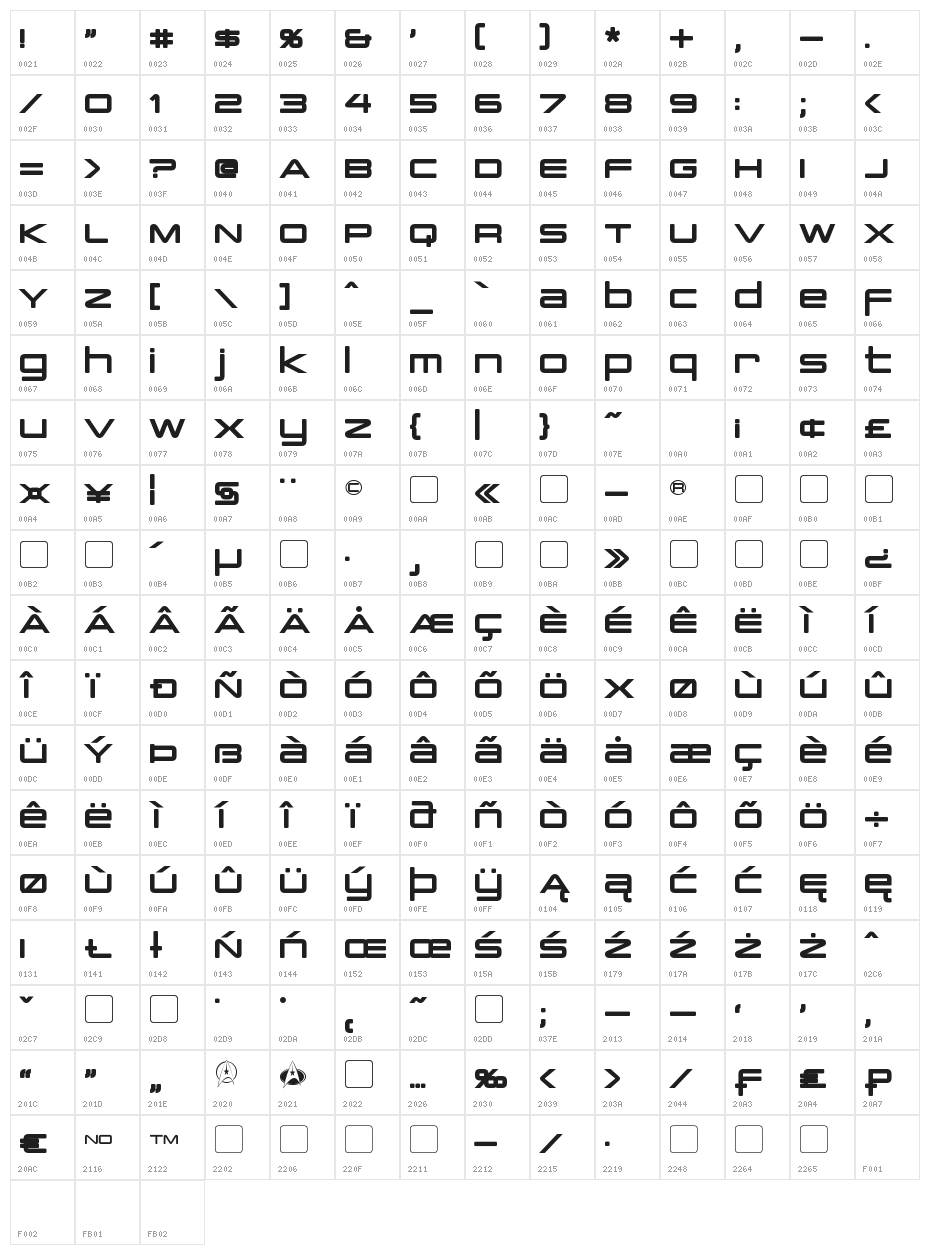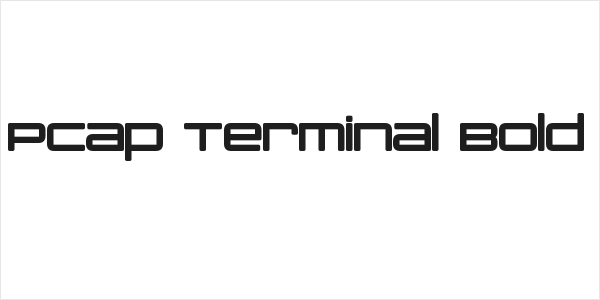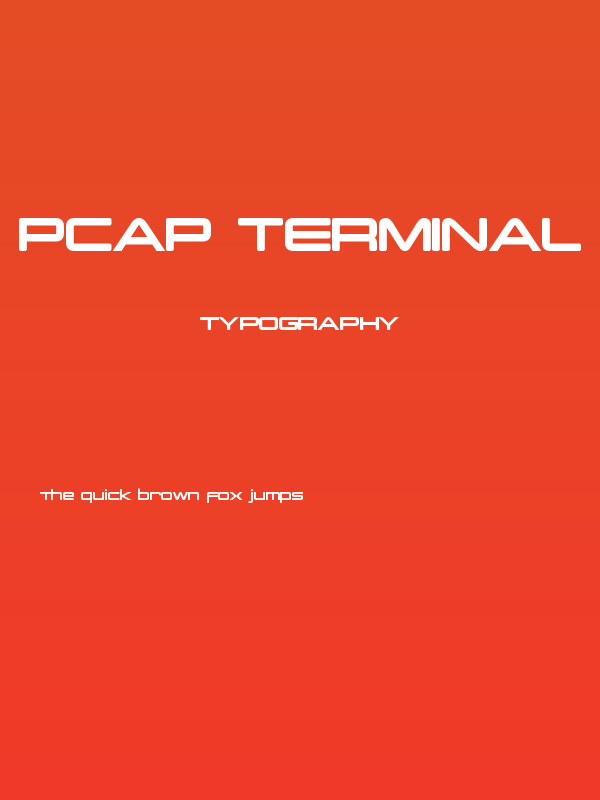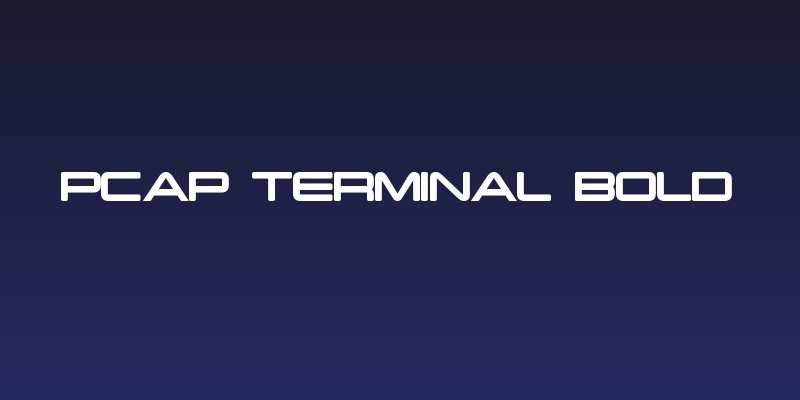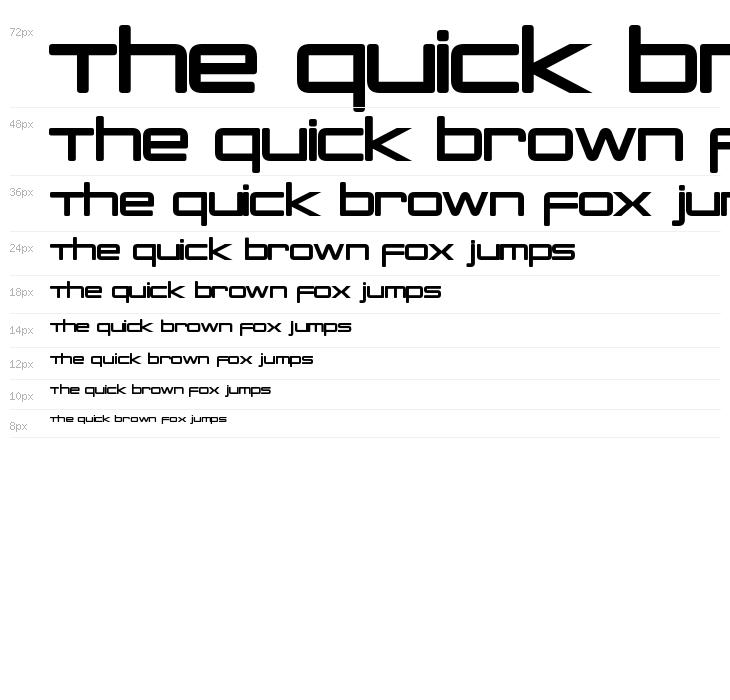
PCap Terminal Bold Font
| Stil general | Futuristic, Geometric |
| Caz de utilizare | Headlines, Logos, Digital interfaces |
| Proiecte propuse | Ideal for technology branding, video game interfaces, sci-fi themed designs, and digital media. |